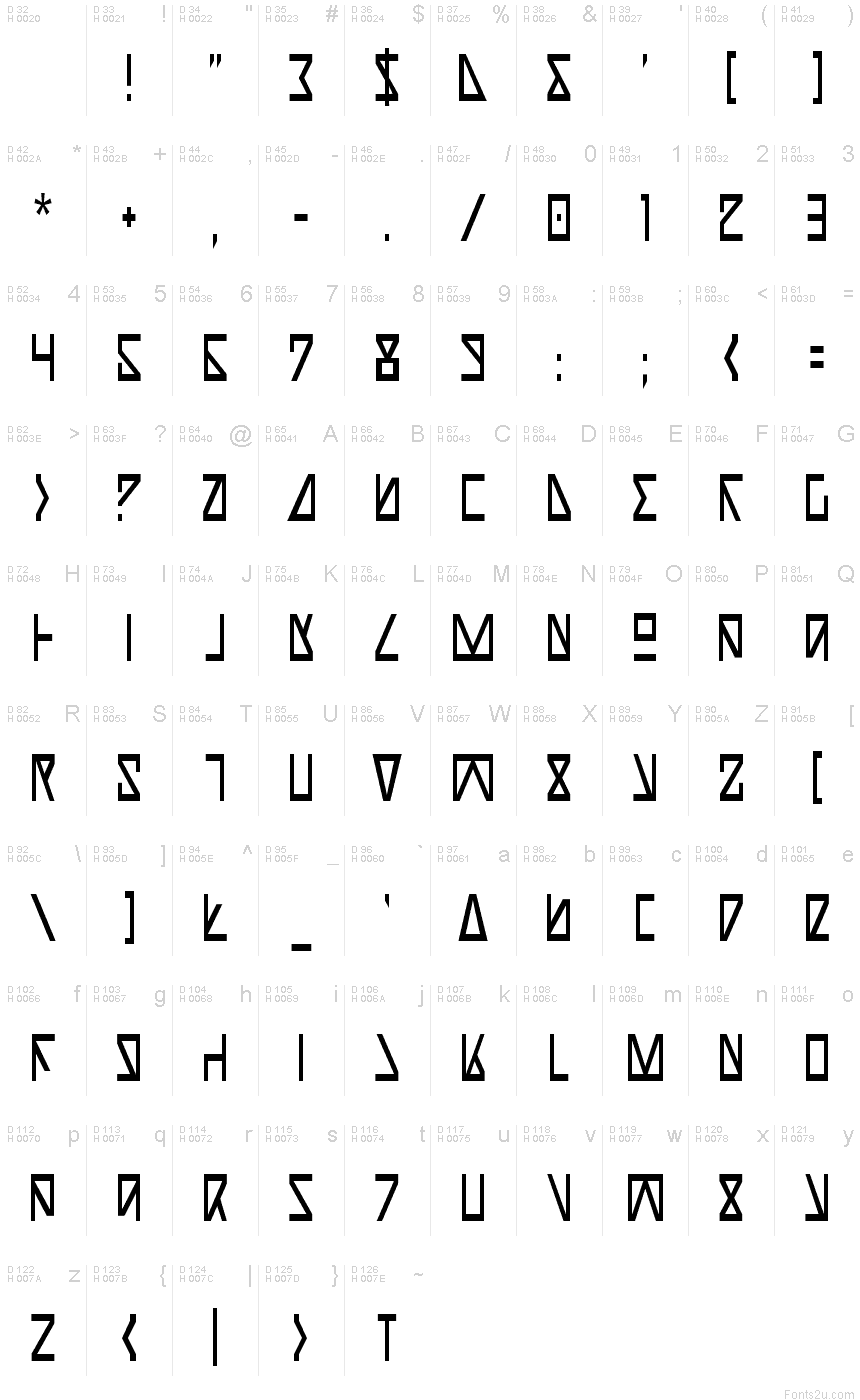
Nick Turbo Condensed od Iconian Fonts to darmowy font techno typu display o ciasnej, pionowej budowie i ostrych, kanciastych cięciach. Litery wykorzystują proste pociągnięcia, twarde narożniki i skośne otwory, co nadaje projektowi mechaniczny, futurystyczny charakter bez zbędnych zdobień.
Nick Turbo Condensed świetnie sprawdza się w grafikach wyścigowych, plakatach sci-fi, tytułach gier, technologicznym brandingu, okładkach albumów i motion designie. Jej skompresowany kształt sprawia, że słowa pozostają zwarte, a kątowe załamania dodają całości napięcia. Ten darmowy font pasuje również do logotypów, wyróżniających się nagłówków i plakatów, gdzie wąski, dynamiczny styl graficzny sprawdza się lepiej niż bardziej miękkie czy tradycyjne kroje.
Nick Turbo Condensed